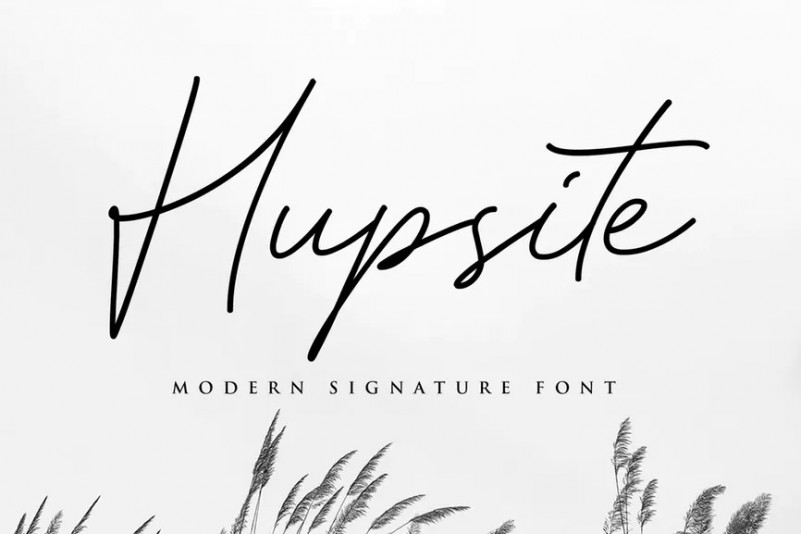
Hupsite Font
Hupsite est un script manuscrit attrayant, idéal pour une utilisation dans des projets qui nécessitent un style organique et naturel. Cette police est idéale pour Logo, logo, image de marque, mariage, mode, étiquette, couverture de livre, t-shirt, poste Instagram, etc., et peut ajouter un look élégant et élégant à votre travail.